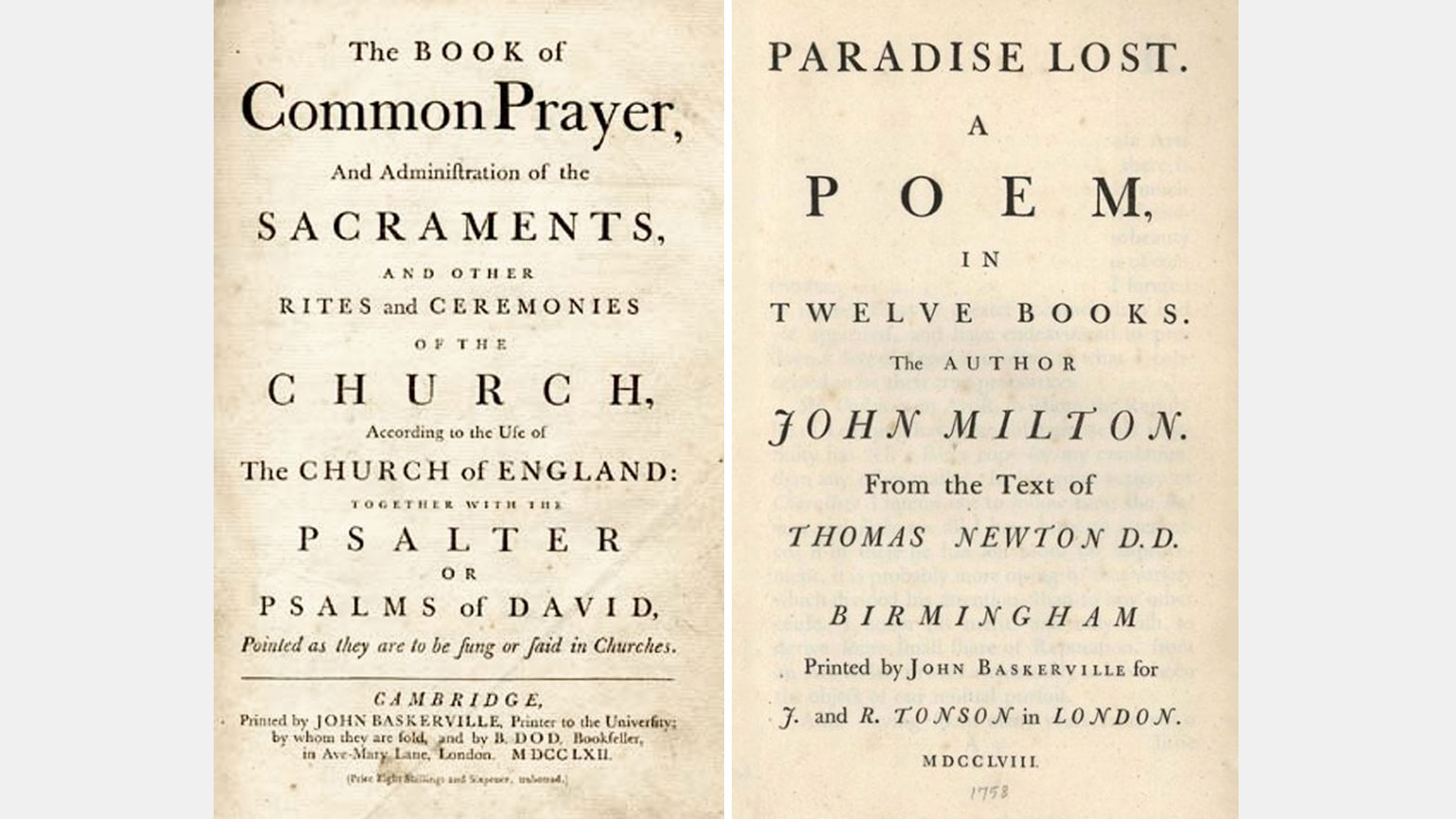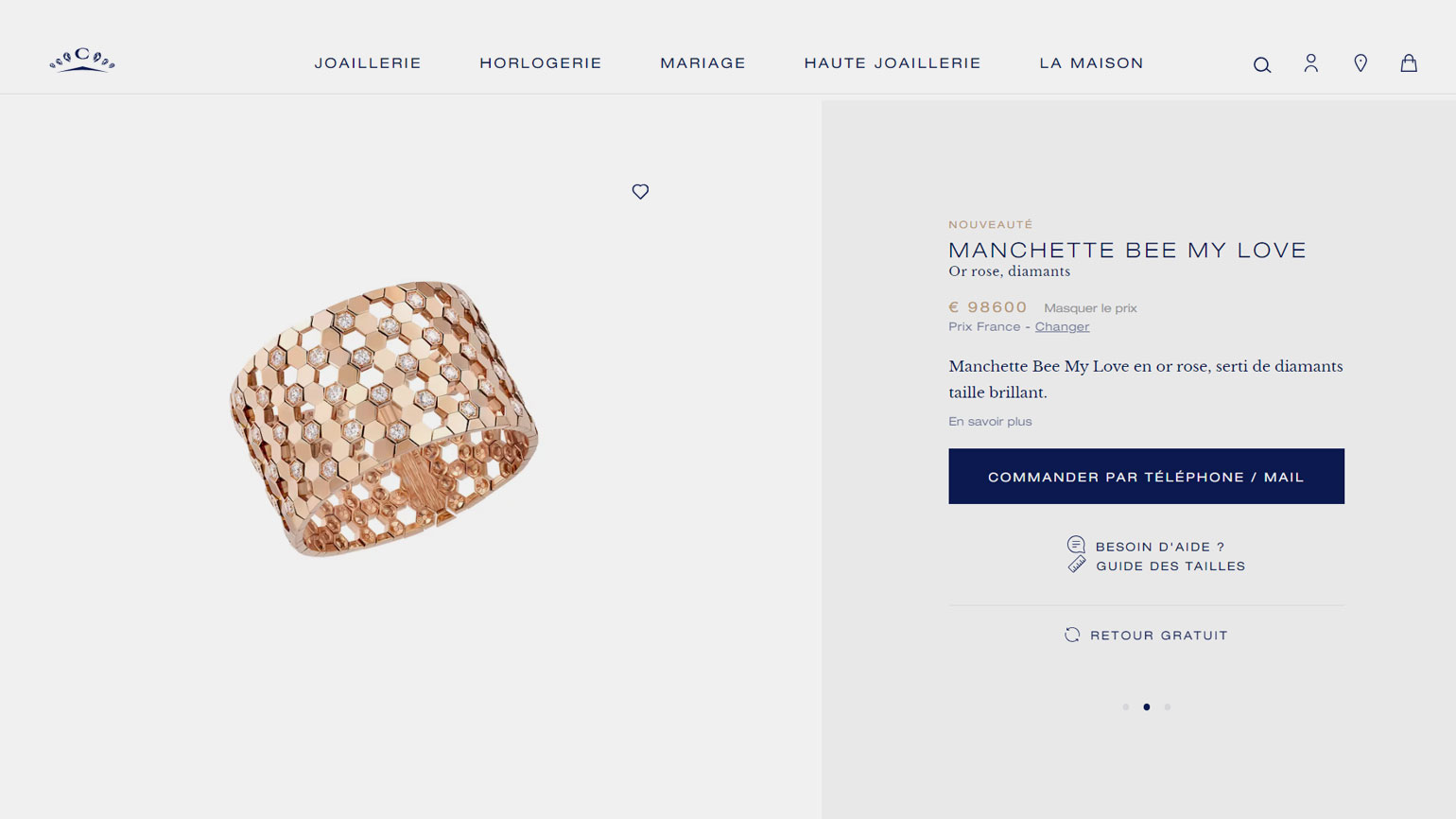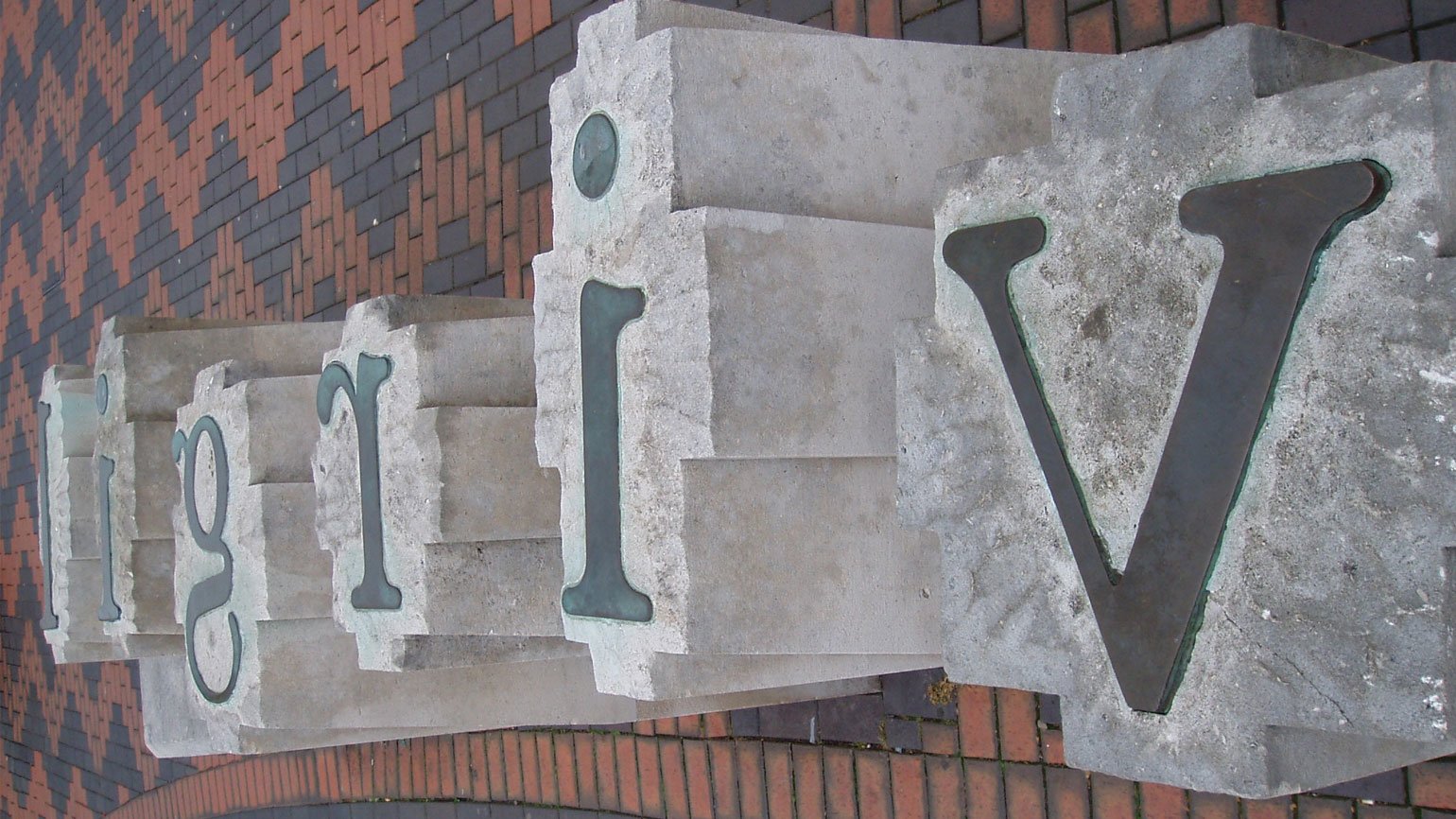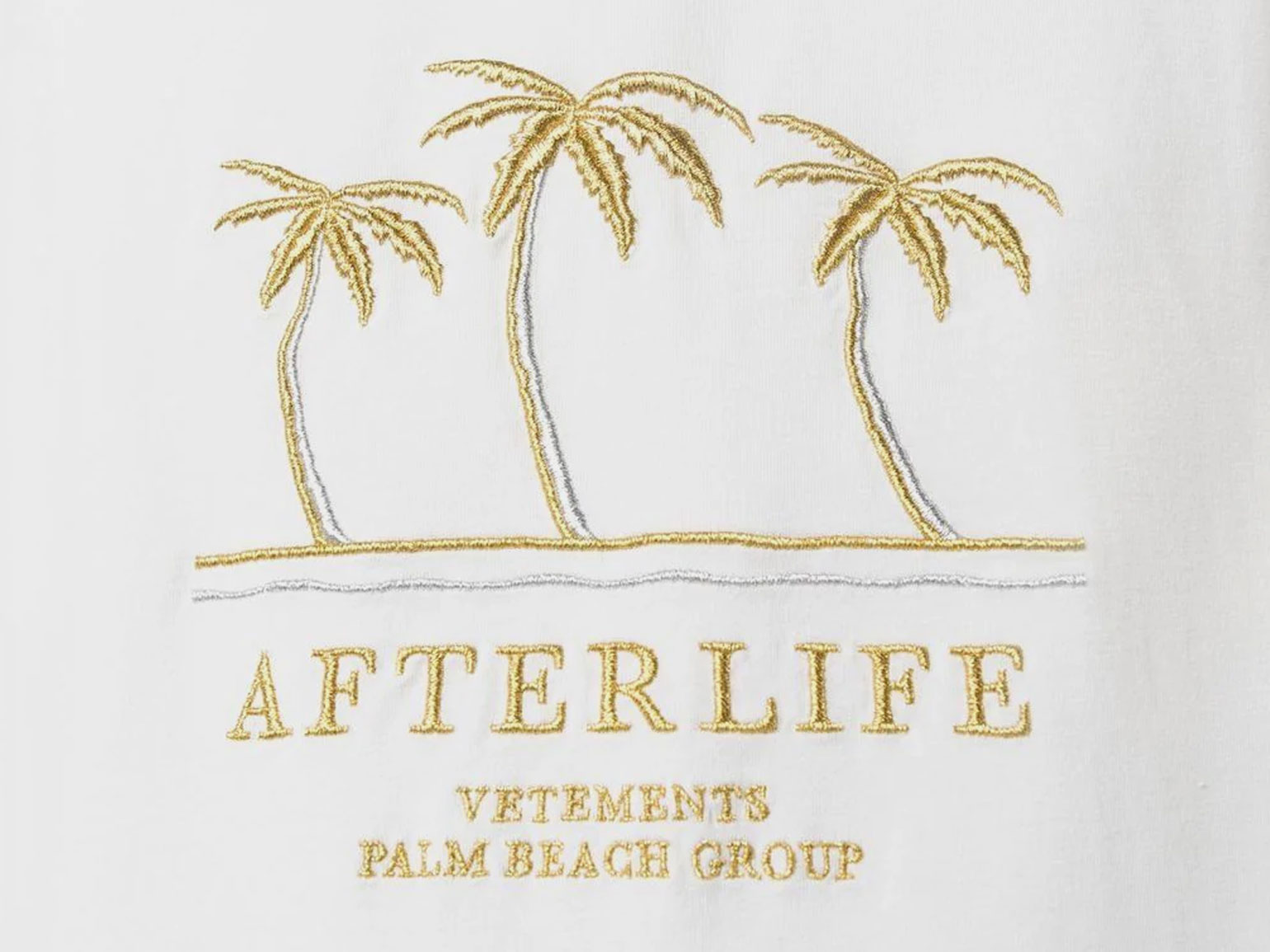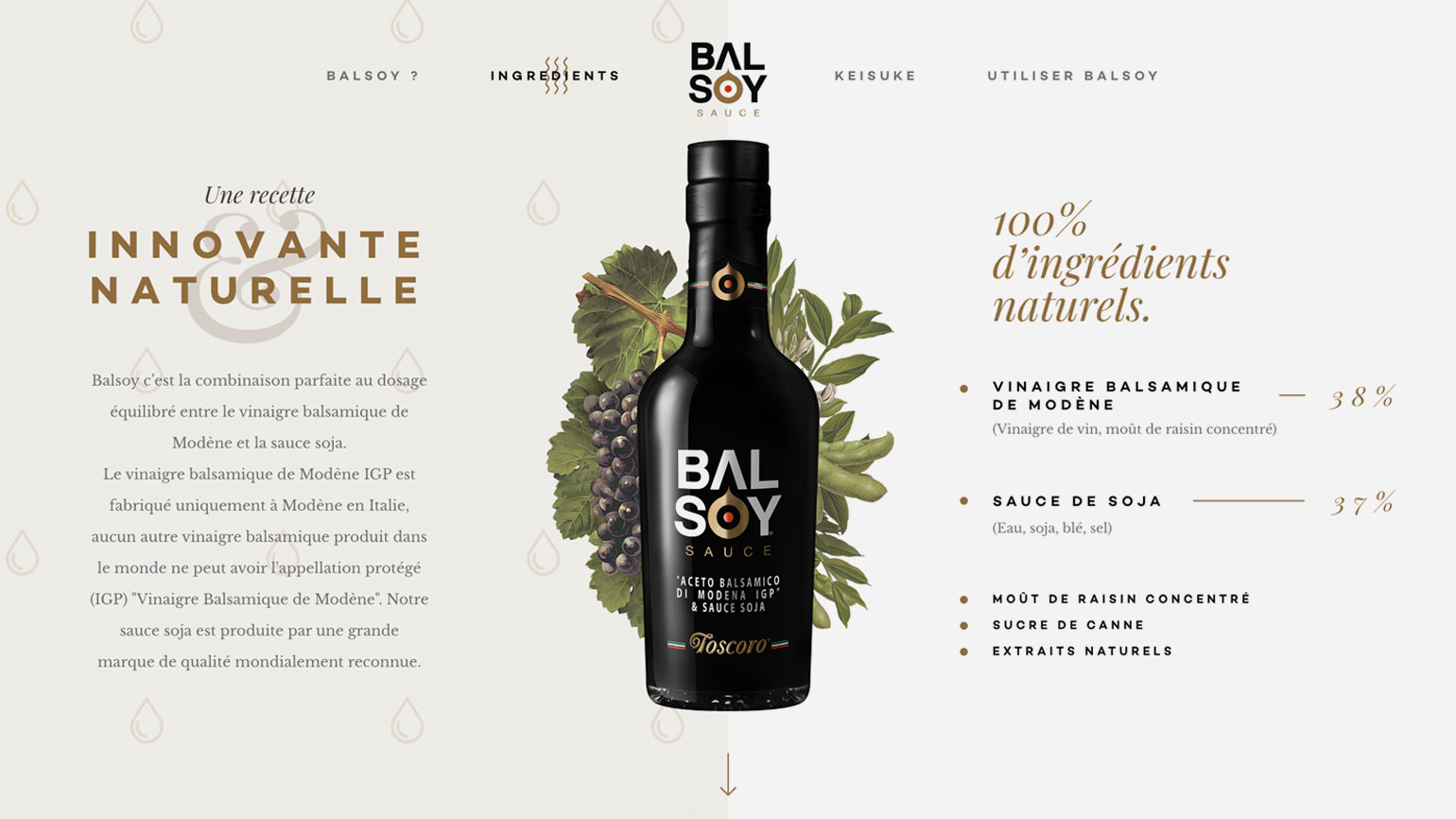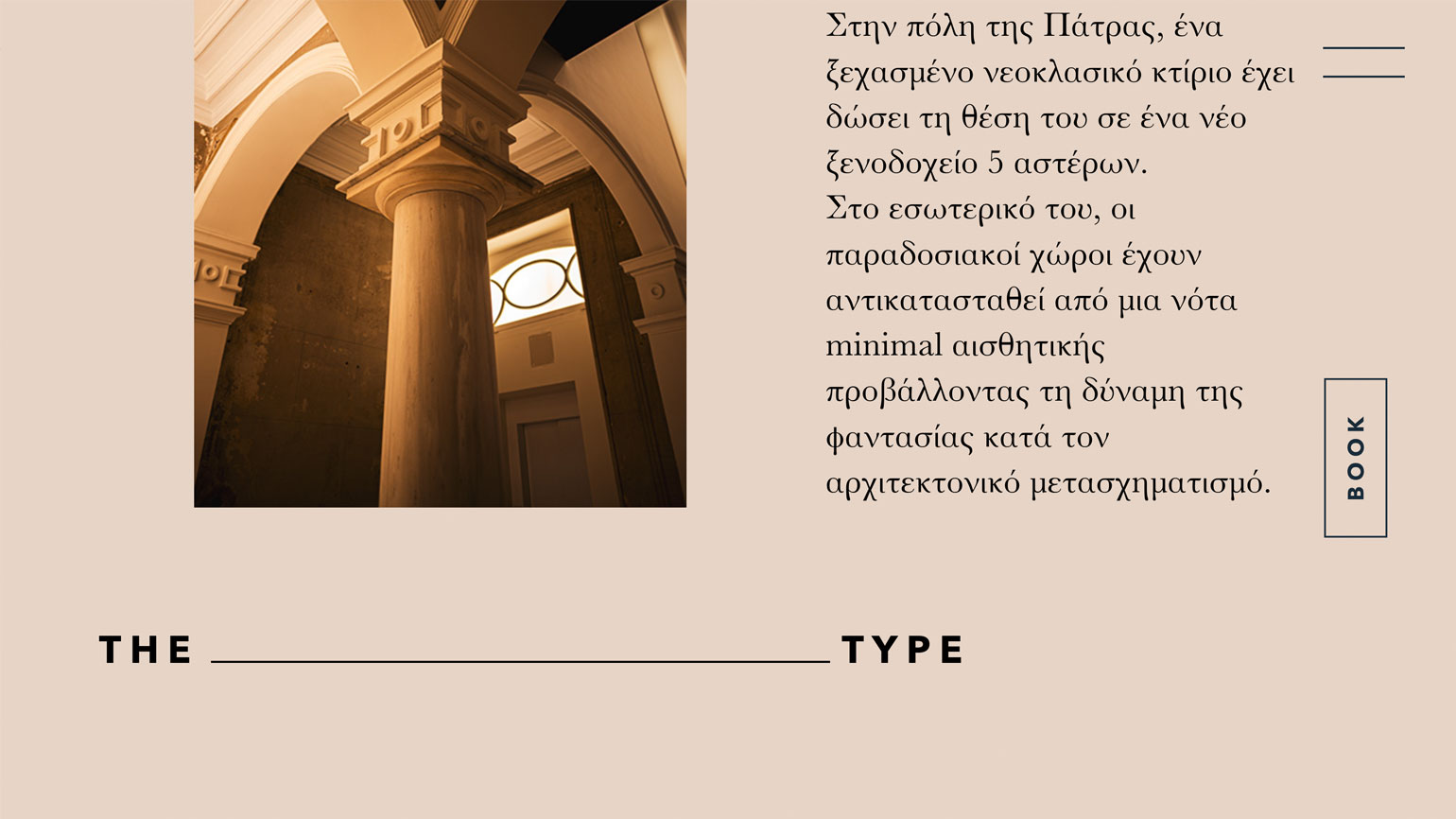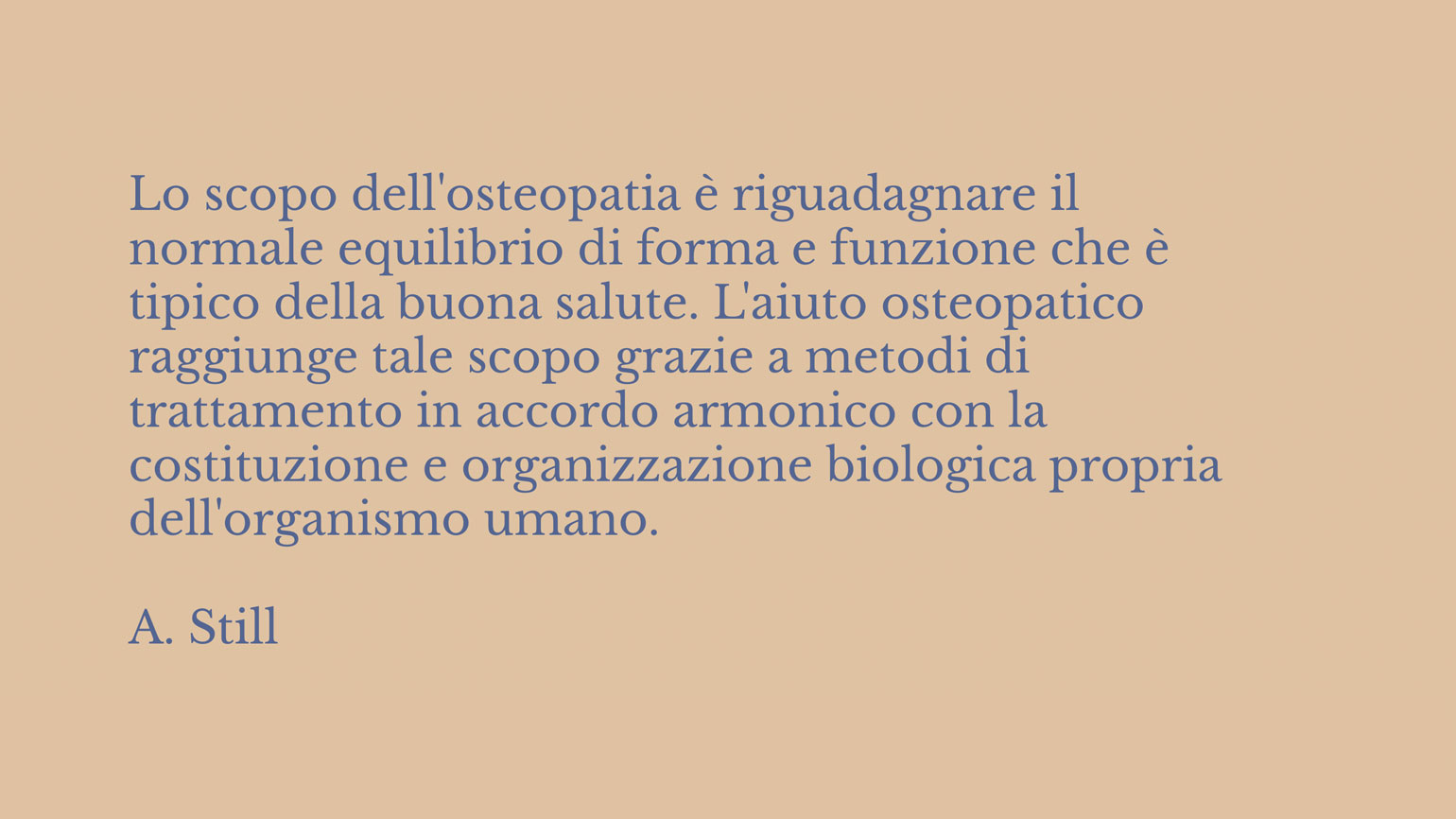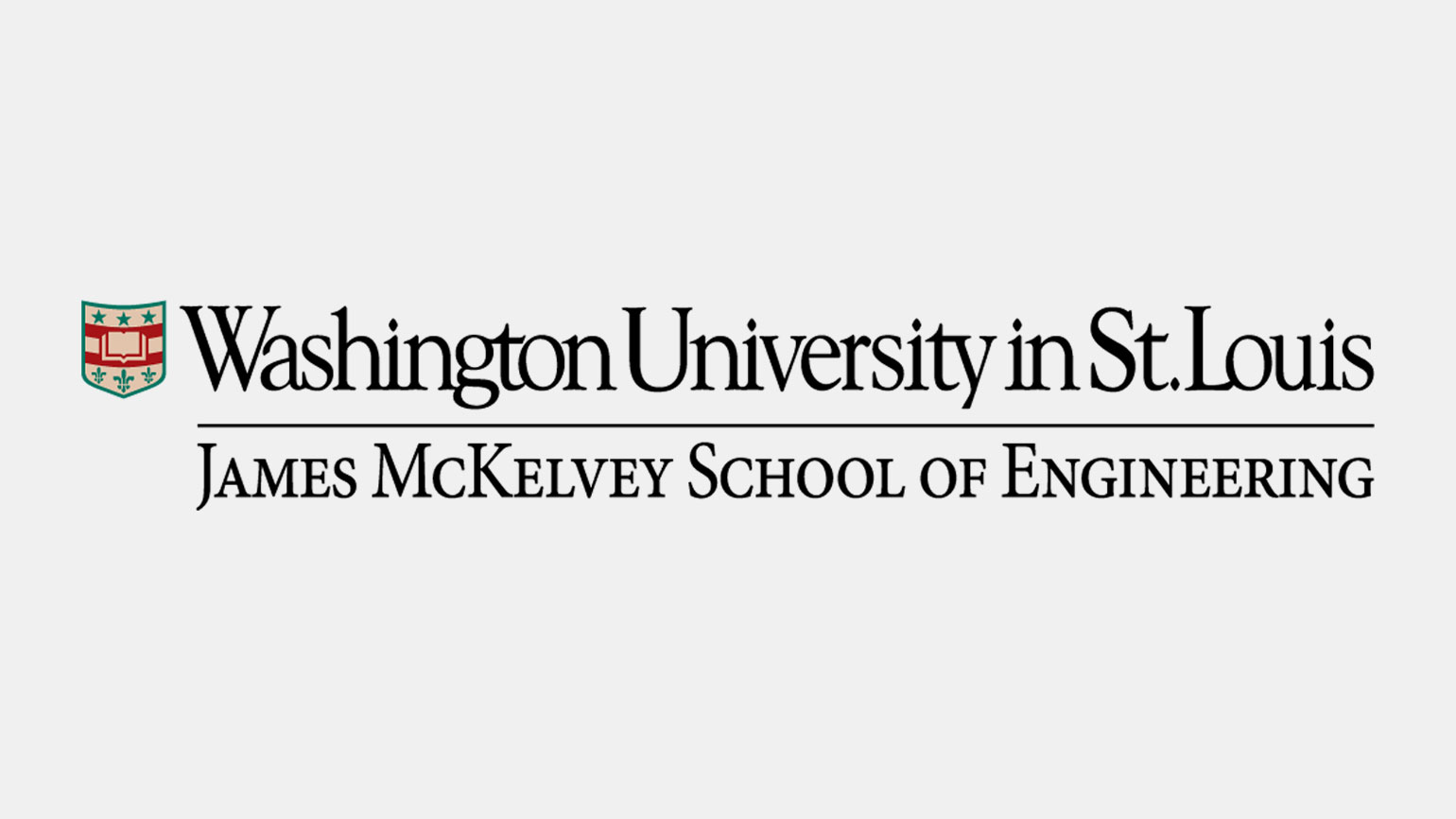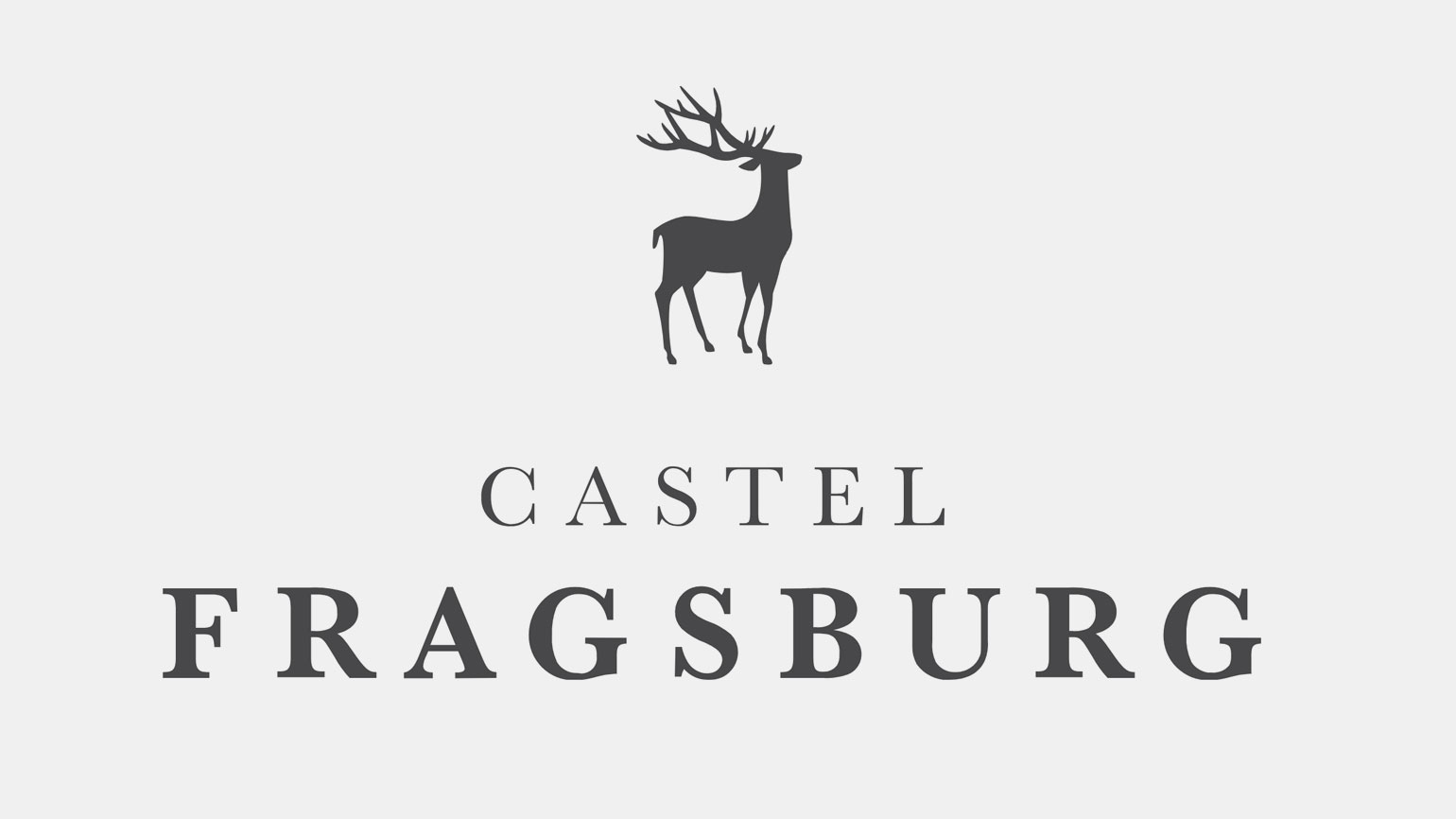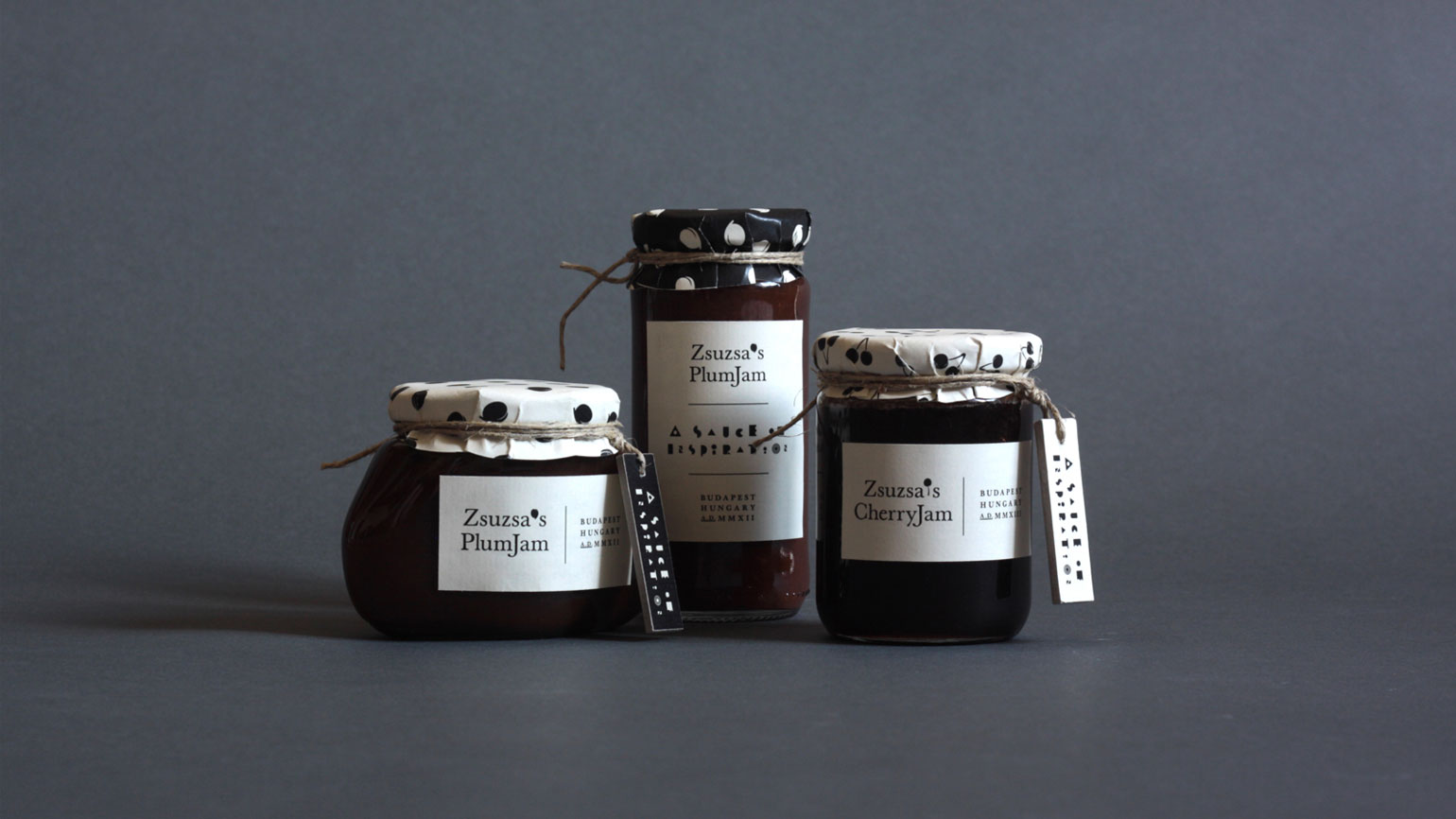
Шрифт Baskerville: где используют и с чем сочетают
Рассказываем об истории Baskerville и показываем примеры удачных шрифтовых пар с ним.
Baskerville — один из старейших образцов шрифтового искусства, который добрался до наших дней практически без искажений. Им набраны сотни тысяч текстов, он знаком миллионам людей и стабильно популярен в дизайне, его считают классическим и даже консервативным. Но так было не всегда: в XVIII веке графика этих букв оказалась революционной.
Baskerville: что это за шрифт
Формальной датой рождения шрифта Baskerville считают 1757 год, когда его автор, типограф и издатель Джон Баскервиль из Бирмингема, выпустил книгу, набранную этой гарнитурой, — собрание произведений римского поэта Вергилия.
Но фактически Джон работал над своим шрифтом семь лет. В молодости он был каллиграфом, учителем чистописания, гравёром надписей на надгробиях, потом создал бизнес по модному тогда «джапанингу» — производству лакированных предметов интерьера в восточном стиле. Именно на этом он заработал достаточное состояние, чтобы открыть собственный издательский и печатный дом и безраздельно заниматься усовершенствованием шрифтов и типографского дела — это произошло в 1750 году. Тогда, почти три века назад, в Англии эти области не были развиты, в отличие от континентальной Европы.
Баскервиль поставил себе задачу сделать максимально легко читаемый шрифт на основе самой популярной в то время гарнитуры Caslon, которую мы сейчас называем антиквой старого стиля. Для этого он не только отрабатывал форму и штрихи в буквах, но и разрабатывал новую, густую и глубоко чёрную краску и экспериментировал с бумагой высочайшего качества. В результате его долгих трудов получился шрифт с более высоким контрастом, чем существовал когда-либо до него: это значит, что визуальная разница между утолщёнными и тонкими штрихами была намного больше привычной.
Впоследствии Baskerville назвали антиквой переходного типа: так обозначили транзит между старым стилем и новым, появившемся во Франции и Италии в конце XVIII века. В этих антиквах нового стиля, Bodoni и Didot, контраст был ещё выше, а графика строже.
Издание Вергилия, которое выпустил Баскервиль, впечатляло качеством, но его шрифт и способ производства не могли немедленно получить широкое распространение и вытеснить старые типографские решения: это было слишком дорого, такой набор и такую печать могли позволить только элитные учреждения и заказчики. Так, в 1758 году Джона Баскервиля назначили официальным печатником Кембриджского университета.
В 1758 году вышло издание поэмы Мильтона «Потерянный рай», в 1762-м — Молитвенник прихожанина, в 1763-м — Библия, где тексты были оформлены гарнитурой Baskerville. Ощутимо увеличенный трекинг — ещё одна находка Баскервиля, которая дошла до наших дней в дизайне книг и научных изданий
После смерти Джона Баскервиля в 1775 году его вдова продала пуансоны и матрицы французам, и шрифт постепенно ушёл в забвение. Только в 1917 году американский дизайнер Брюс Роджерс обнаружил книгу, набранную Baskerville во французской словолитне Bertrand. Под руководством Роджерса эти формы нашли и в 1919 году продали типографии Гарварда, и с тех пор популярность шрифта стала быстро расти — не в последнюю очередь благодаря тому, что Baskerville стал ассоциироваться с престижным университетом и высоким статусом.
Памятник шрифту под названием «Индустрия и гений» в Бирмингеме
Выверенная антиква Baskerville действительно оказалась одной из самых легко читаемых. В XX веке ей стали набирать длинные тексты, использовать её в дизайне рекламы, которую нужно разбирать издалека. Хотя в этом шрифте достаточно декоративных деталей:
• хвост-шлейф у Q;
• резко заострённые засечки;
• рукописные изгибы в курсиве;
• похожий на цветок курсивный &.
Сейчас Baskerville, как правило, воспринимают как символ элегантности и старинного достоинства. Благодаря визуальному флёру прекрасного исторического прошлого к этому шрифту обращаются, когда необходимо создать впечатление, что за текстом или айдентикой стоит богатое — или академическое — наследие.
Шрифтовая пара Nitti Grotesk и Baskerville на сайте сети ресторанов-остерий Gucci
Скриншот: сайт Gucci Osteria / Skillbox Media
Тексты на сайте врача-остеопата оформлены Baskerville. Так создаётся впечатление академичности и почтенности
Скриншот: сайт Alessandra Chiari / Skillbox Media
Вышивка шрифтом Baskerville на футболке Vetements. Afterlife переводится как «загробная жизнь»
Baskerville — один из фирменных шрифтов очень дорогого ювелирного дома Chaumet
Сейчас распространено несколько шрифтовых семейств, которые основаны на оригинальном Baskerville:
• ITC New Baskerville 1978 года, автор Джон Кваранта. Графика повторяет первую версию гарнитуры Джона Баскервиля, которую он представил в 1724 году. Кириллицу для этого семейства разработал в 1993 году Тагир Сафаев.